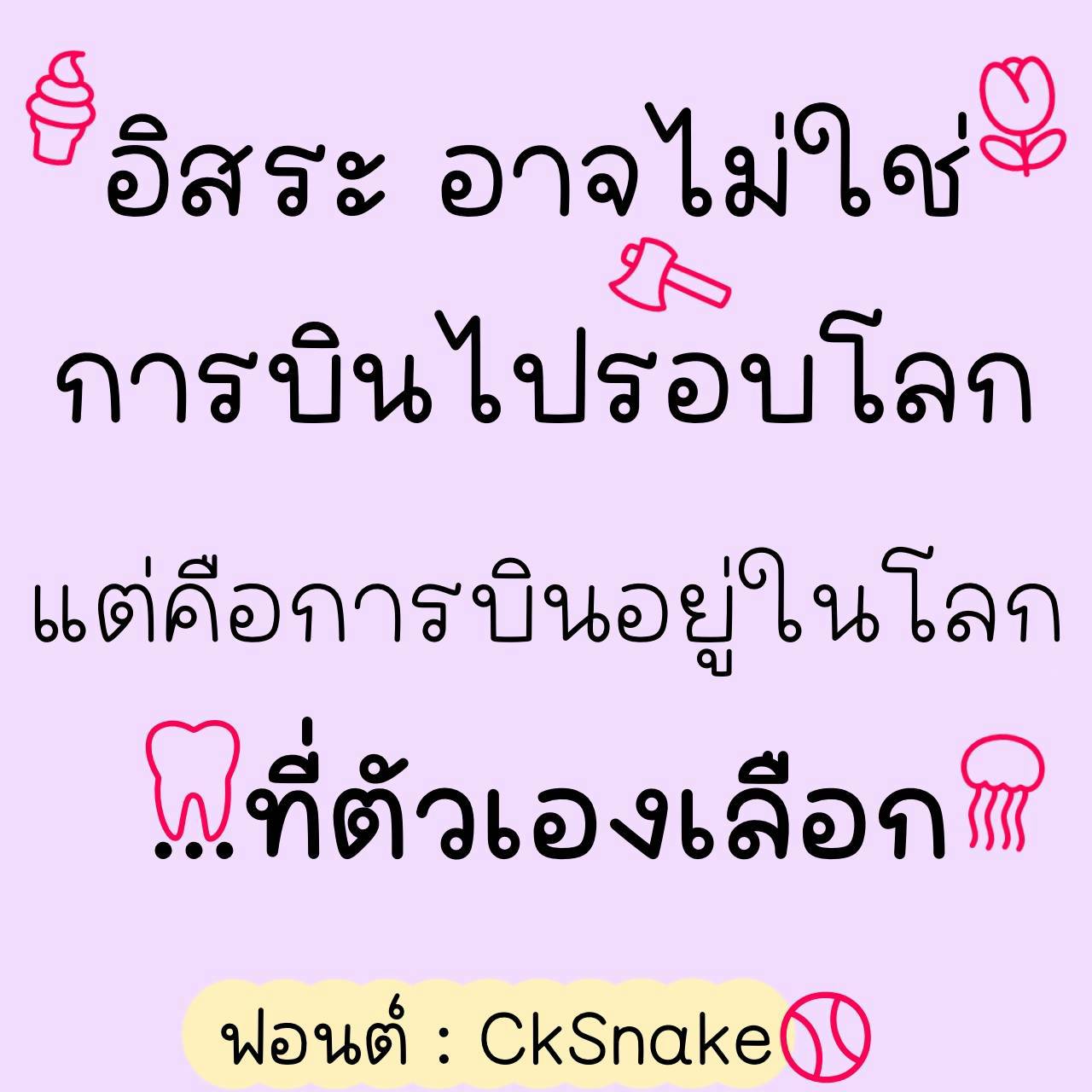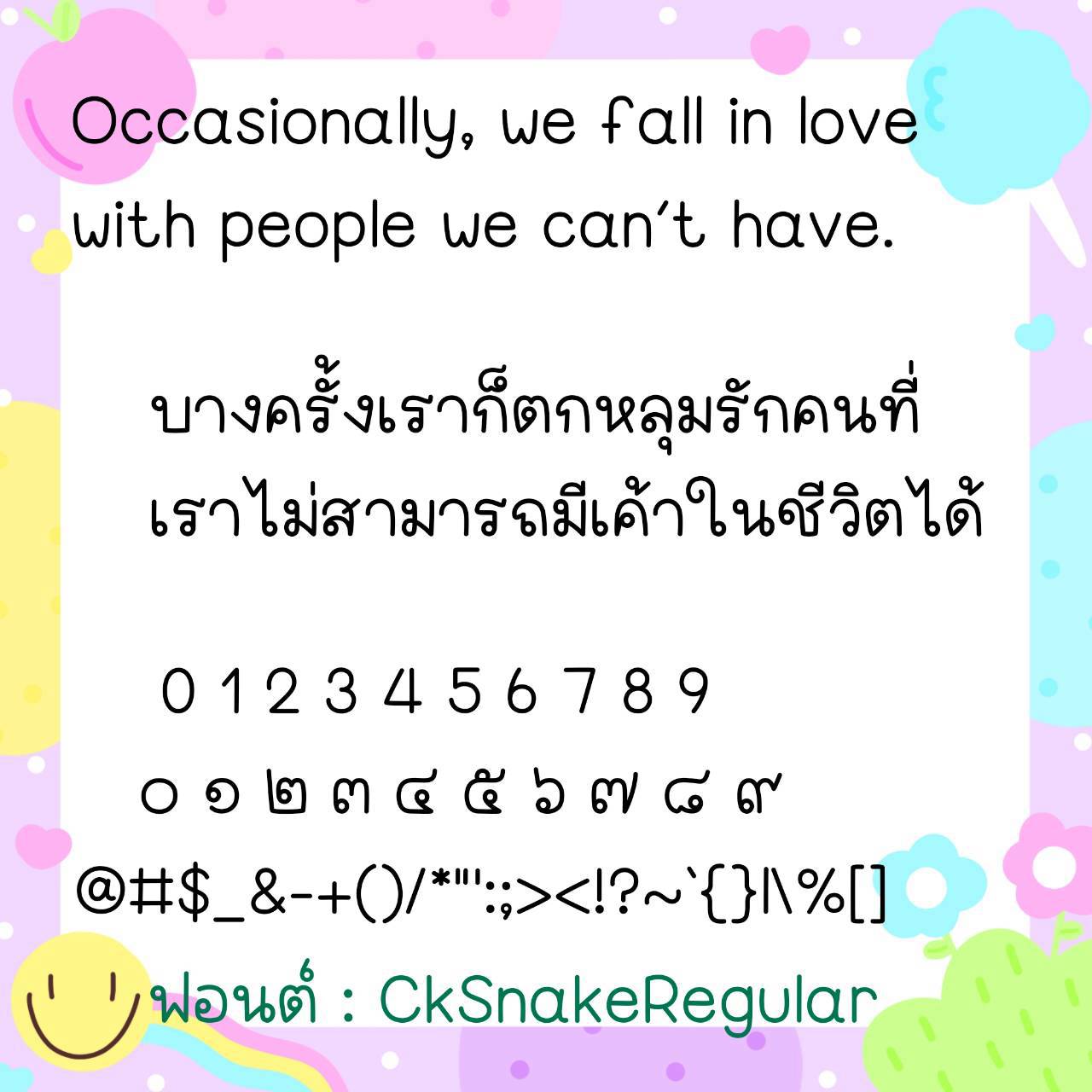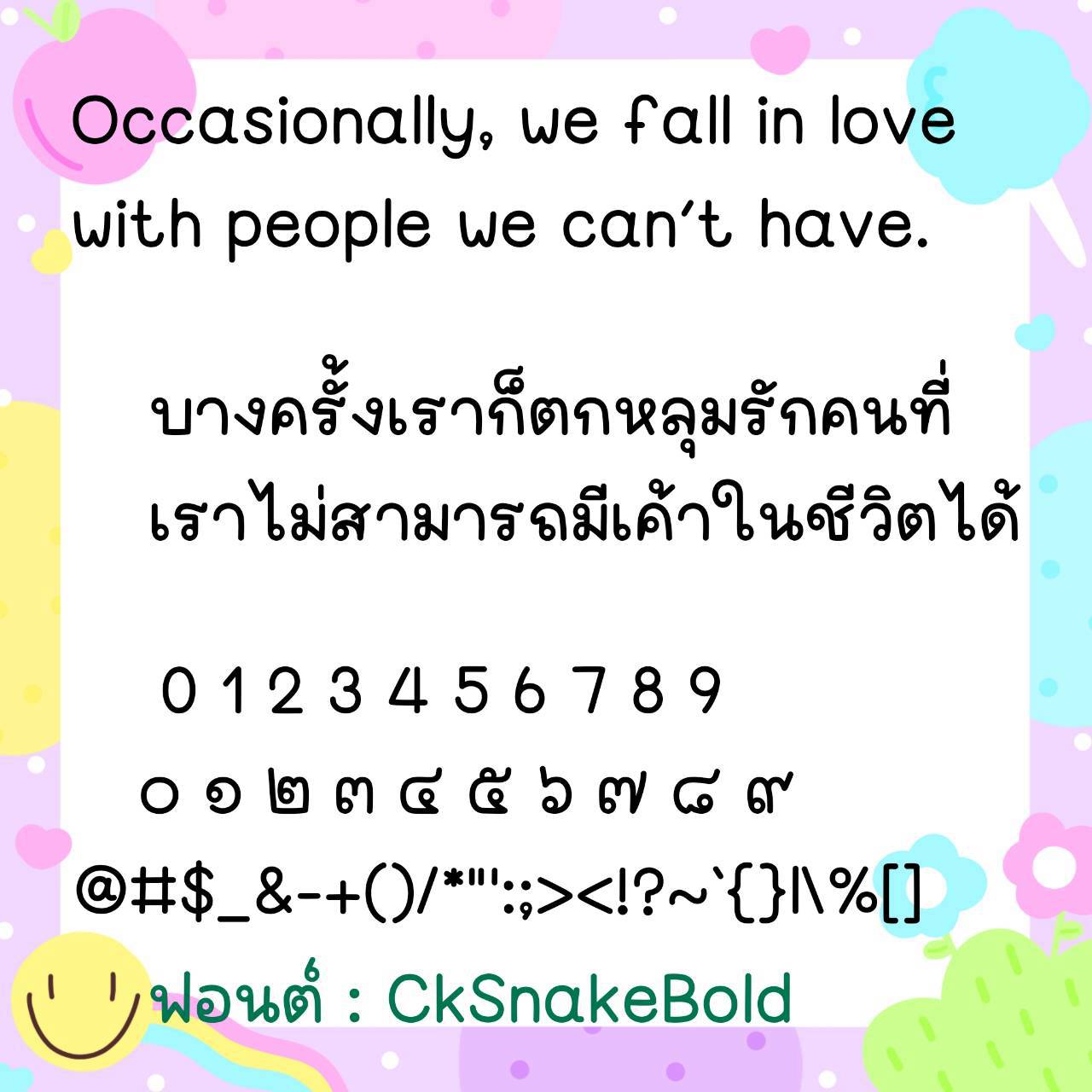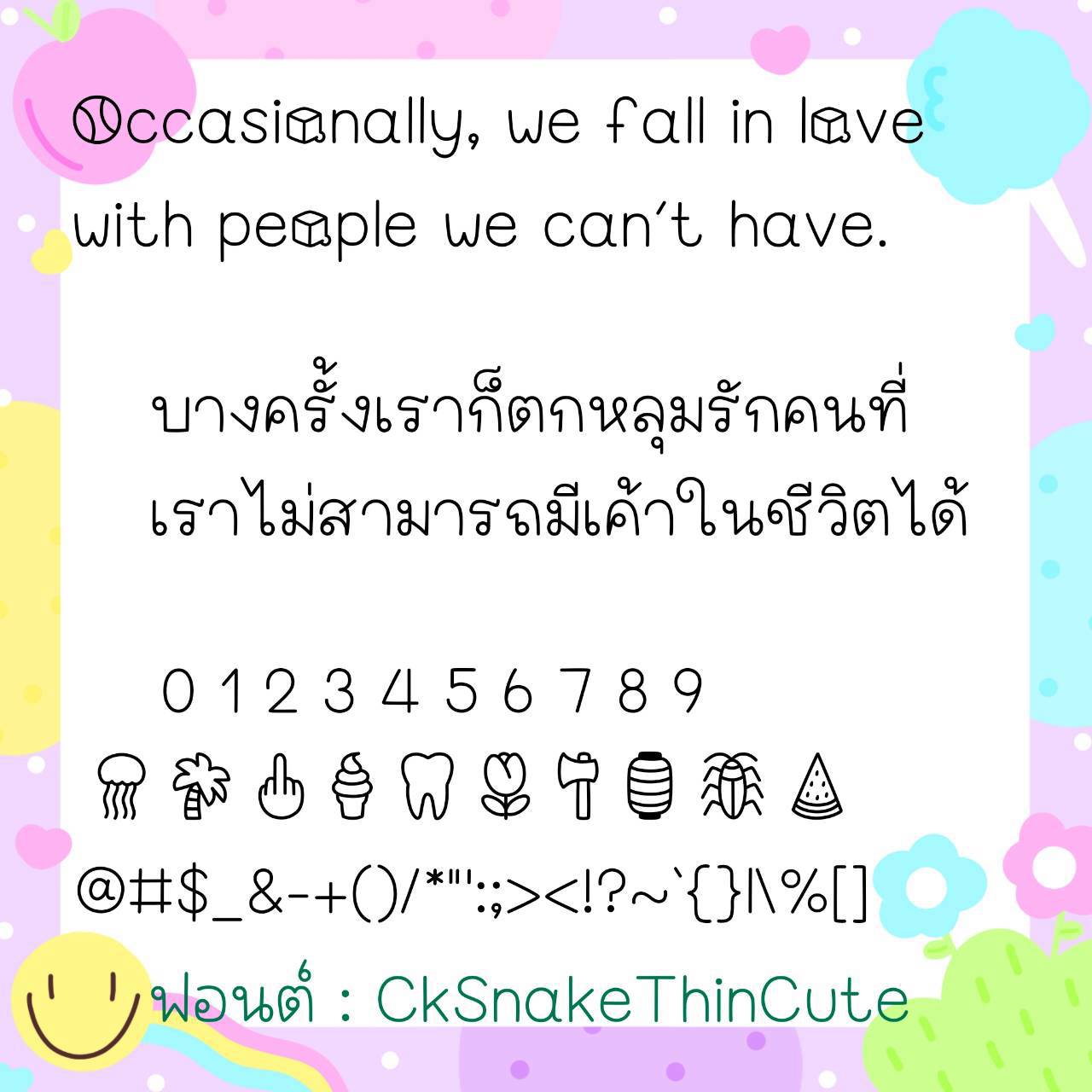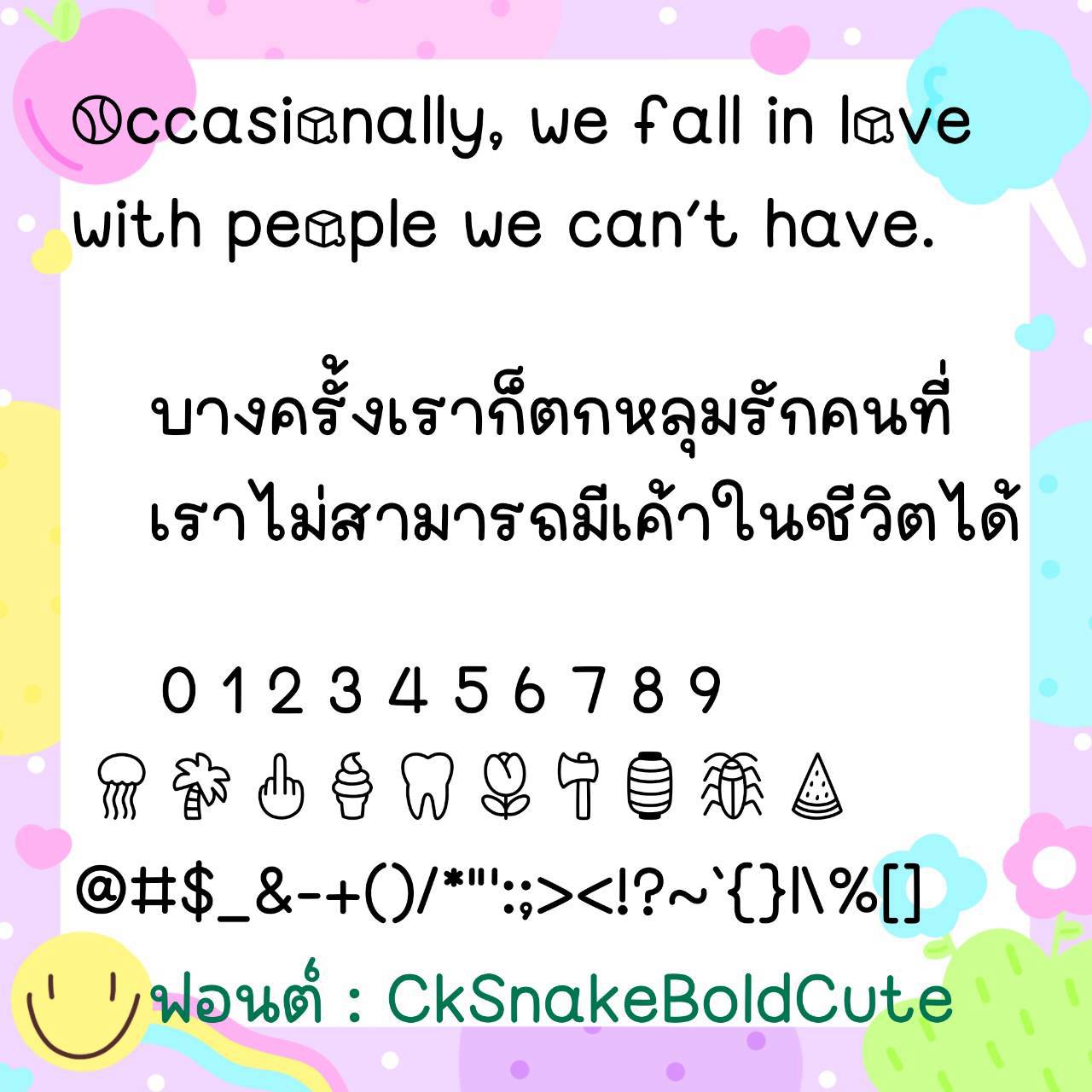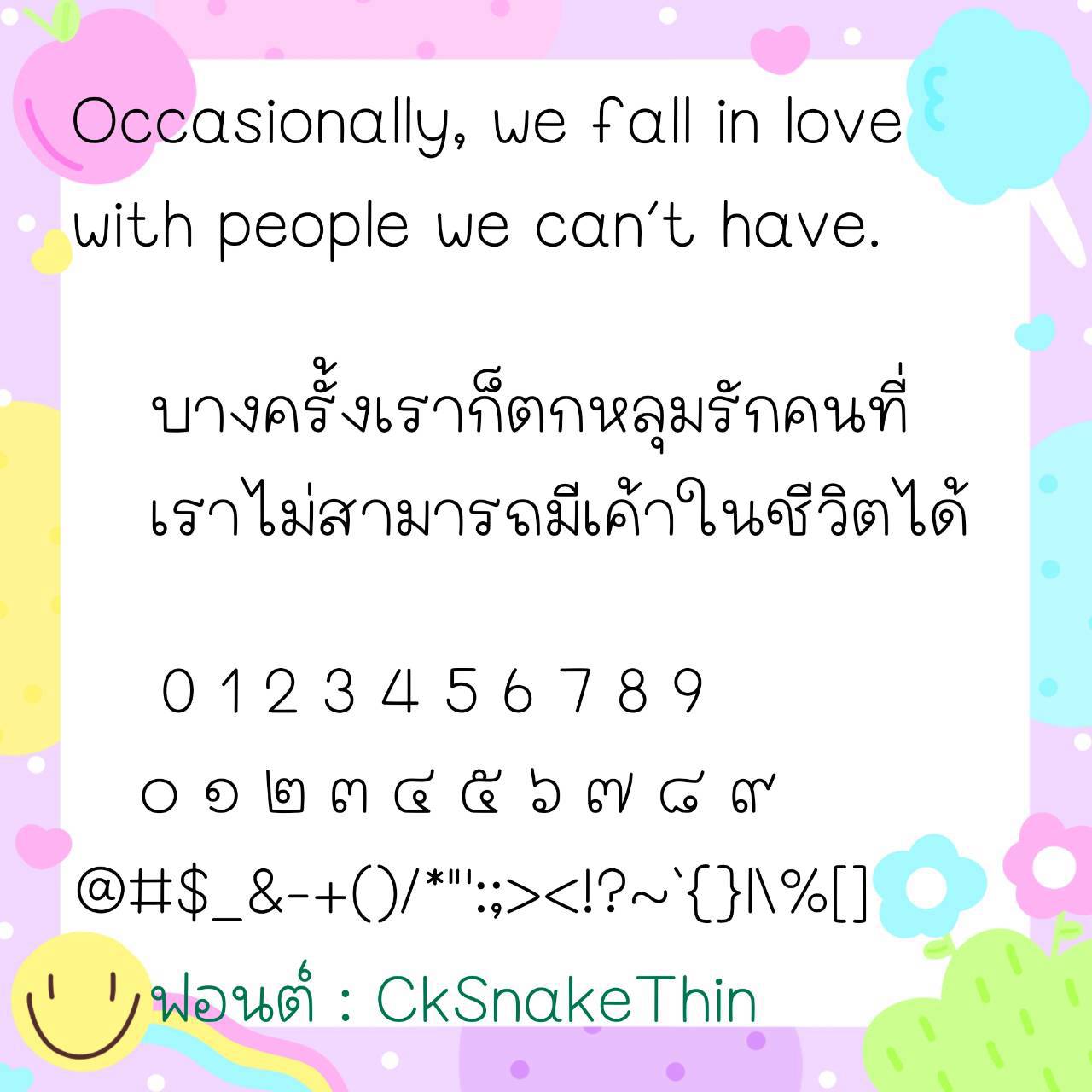
Font CkSnake
🔸 ฟอนต์ลายมือแนวน่ารักแบบวัยรุ่น เป็นฟอนต์ตัวอ้วนกลม อ่านง่ายสบายตา และยังมีไฟล์อิโมจิน่ารักๆที่ใช้แทนเลขไทยให้ด้วยค่ะ 🥰💙
🔹 This is a cute, youthful handwritten font. It’s a chubby, round font that’s easy on the eyes, and it also includes cute emoji files that can be used to replace Thai numerals. 🥰💙